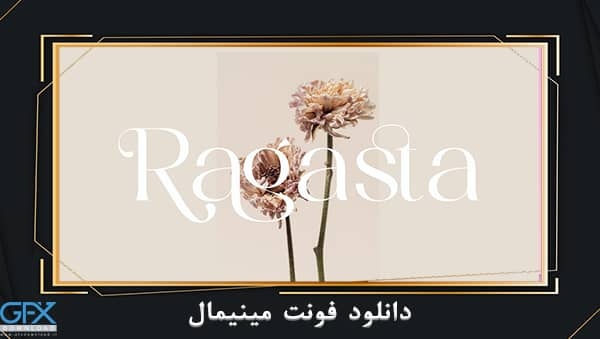
دانلود فونت مینیمال رایگان Ragasta Minimalist
فونت مینیمال انگلیسی رایگان Ragasta Minimalist
دانلود رایگان فونت مینیمال انگلیسی Ragasta Minimalist
در این پست با معرفی یکی از فونت های کاربردی و زیبا به سبک مینیمال با شما همراه هستیم که به صورت کاملا رایگان در سایت برای دانلود قرار داده شده است. دانلود فونت مینیمال رایگان Ragasta Minimalist یکی از فونتهای ساده در عین حال زیبا است که برای تکمیل محصولات خلاقانه دیجیتالی و چاپی شما مناسب است. این فونت برای پوسترها ، پست های رسانه های اجتماعی ، نام تجاری ، پروژه های شخصی و غیره مناسب است. شامل فایلها OTF، WOFF، TTF می باشد.